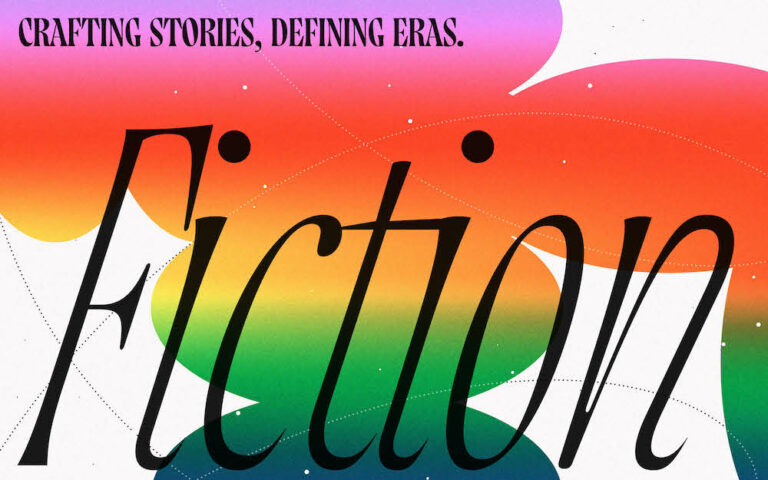
Spitz und ausladend, sanft und lyrisch: Die neue Schrift Gregory Poster der TypeMates, die in einer internationalen Kollaboration entstand, ist nichts für Verzagte.
Die TypeMates Jakob Runge, Nils Thomsen-Habermann und Lisa Fischbach sind über ganz Deutschland verteilt und arbeiten so erfolgreich für Kunden wie Der Spiegel, Lego, Mutabor, Jung von Matt oder den FC Bayern München – und schließen sie beim Entwerfen von Schriften gerne auch mal mit anderen Schriftgestalter:innen zusammen.
So wie TypeMates Gründer Jacob Runge, der im Landkreis Passau lebt, jetzt mit George Triantafyllakos aus Thessaloniki und Seryozha Rasskazov, der, in der Ukraine geboren, heute in Lausanne zu Hause ist.
Und auch die beiden haben schon immer gerne über den Typo-Tellerrand hinausgeschaut: Triantafyllakos, der mit einem Doktor in Informatik auch als Webentwickler arbeitet und Rasskazov, der Brandings entwickelt, Lettering-Künstler ist und eine Leidenschaft für Plakatkunst hat, samt umfassender Sammlung.
Mit ihnen arbeitete Jakob Runge an der neuen Schrift Gregory Poster, einer Flared Serif, die so prägnant wie exzentrisch ist.
Schönste Widersprüche
Fast wie Stacheln wirken die Serifen, sind lang und spitz zulaufend, haben kunstvolle Querstriche und dazu dann wieder lyrisch geschwungene Rundungen. In eindrucksvoller Höhe schweben die Punkte über dem i, erinnern Abstriche an Schwerter, um dann auf ein o zu treffen, das sich in schönster Harmonie wölbt.
Mit der Gregory Poster setzt das Typografen-Trio auf Authentizität, darauf, sich selbstbewusst abzuheben und auch seine Unvollkommenheit zu leben.
Und auch einen Hauch Nostalgie sehen sie in ihr.
»Wie ein schickes Second-Hand-Sofa versetzt Gregory den Betrachter in warme Erinnerungen an eine frühere Zeit und einen früheren Ort«, heißt es von den Kreativen. Und gleichzeitig erinnert sie die Gregory Poster an die Schriftzüge alter Bucheinbände, die durch die ausladenden Striche noch akzentuiert werden.
Ausgelassene Vielfalt
Besonders aufregend sich auch die kursiven Buchstaben, die sich in einem dramatischen Winkel von 18 Grad neigen.
Von Triantafyllakos und Rasskazov wurde die Schrift darüber hinaus auch in Griechisch und Kyrillisch gezeichnet und ist, einschließlich Vietnamesisch, in über 270 Sprachen erhältlich.
Gleichzeitig verfügt sie über mit einer Reihe von OpenType-Features über eine eindrucksvolle Vielzahl von Icons, Symbolen, sprachspezifischen Lokalisierungen und Emojis.